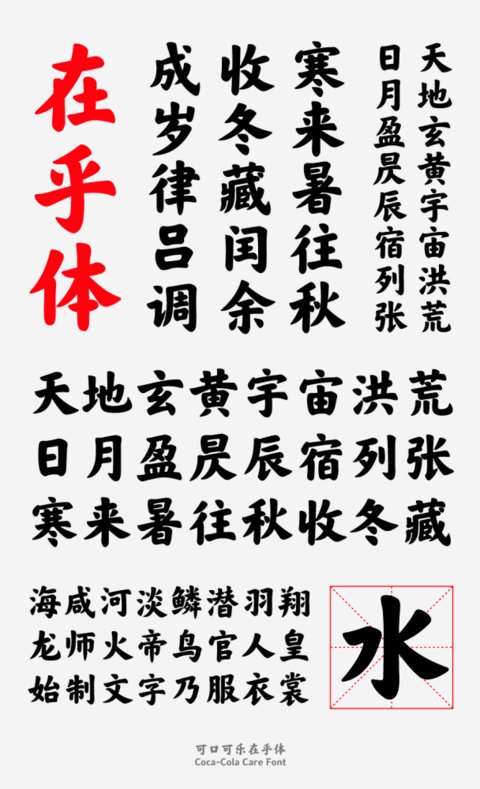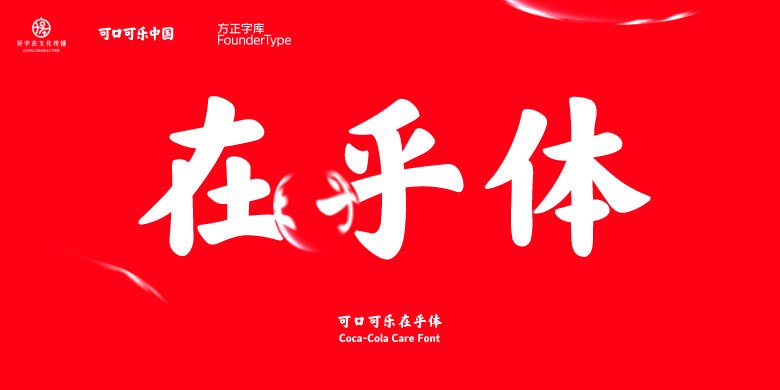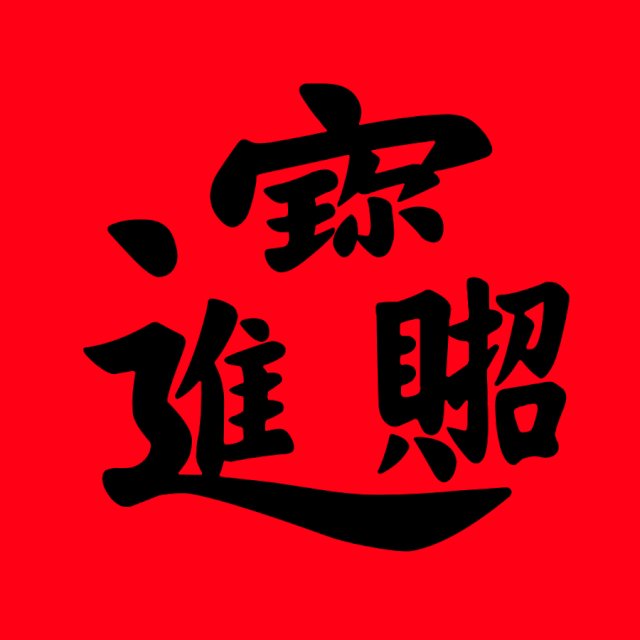
【可口可乐-在乎体】可口可乐字体 | 官方发布商业字体 | 提供字体包免费下载非商业使用
可口可在乎体字体
可口可在乎体字体、
可口可在乎体字体
可口可乐中国官微给出的消息称,赶在这个特殊的时刻,送大家一套“可口可乐在乎体”字体,而字体灵感灵感来源于可口可乐重返中国时所用的经典商标,经过一年多的悉心打磨,包含7745个字符(汉字6769个,其他字符976个)的“可口可乐在乎体”终于面世。
字体名称:可口可乐在乎体
字符数量:7745个字符(汉字6769)